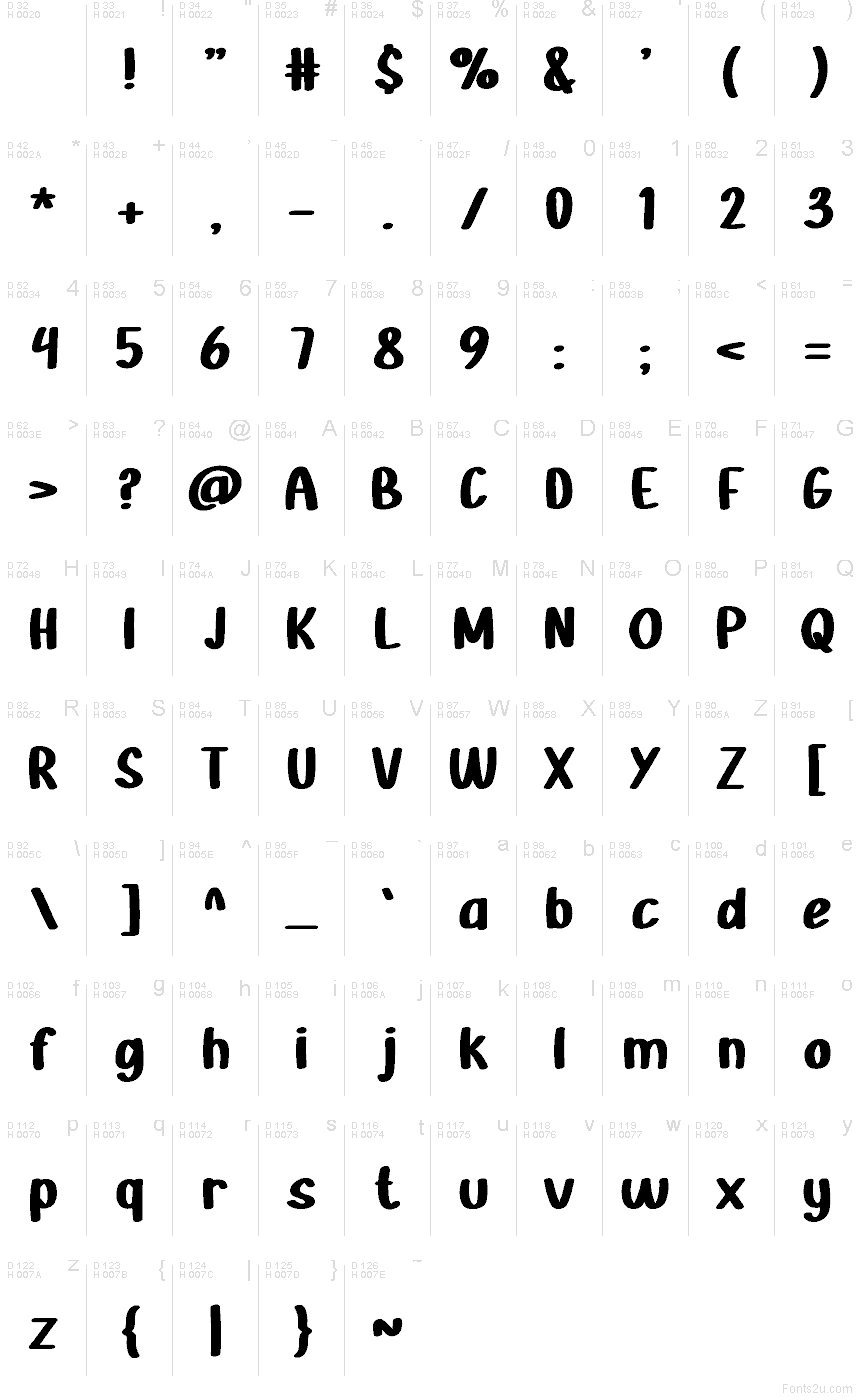
RIVERSEA
Písmo Riversea od Pinisiart je bezplatný font písaný rukou s vysokými, zaoblenými písmenami a jemne nepravidelnými okrajmi, ktoré mu dodávajú autentický ručne kreslený vzhľad. Tvary zostávajú jednoduché a otvorené, ale vďaka variabilite ťahov text nepôsobí mechanicky.
Riversea skvele funguje v logách, nadpisoch plagátov, na obaloch, v citátových grafikách aj na sociálnych sieťach, kde potrebujete osobnejší nádych. Tento bezplatný font sa hodí aj na remeselné etikety a neformálny branding, pretože jeho uvoľnený a istý rytmus pôsobí prirodzene, bez toho, aby bol neprehľadný.